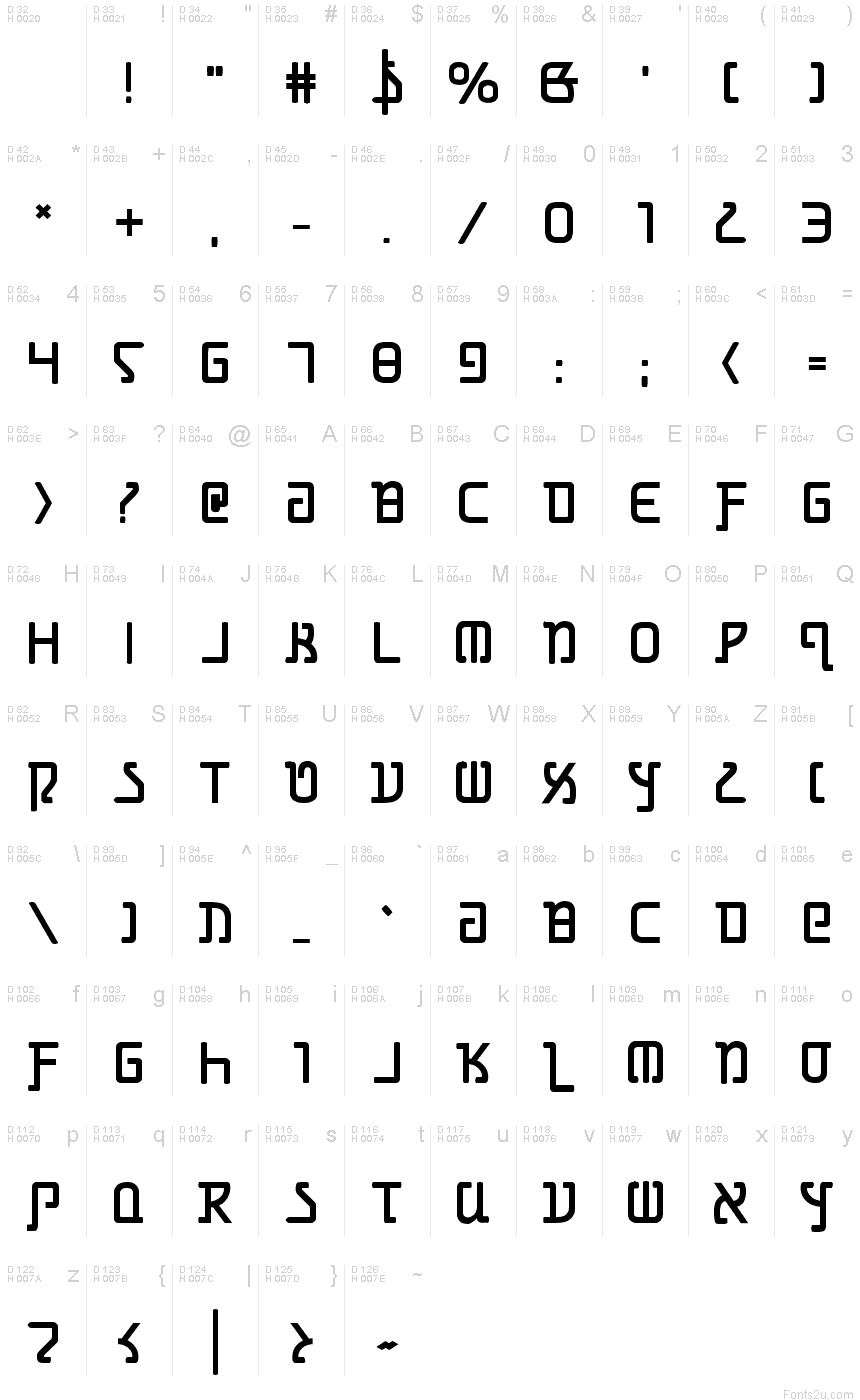
Grimlord Bold, progettata da Iconian Fonts, è un carattere display retro-futurista gratuito con lettere ampie e squadrate. Gli angoli esterni arrotondati incontrano tagli netti e strette interruzioni simili a stencil, conferendo alle lettere una struttura modulare e meccanizzata. I tratti densi e le giunzioni insolite ricordano i pannelli di controllo e l'hardware fantascientifico.
La grafica dei videogiochi rappresenta un contesto naturale per la sua geometria industriale, in particolare nelle etichette delle interfacce, nelle schermate dei titoli e nei poster promozionali. Si adatta inoltre al packaging di musica elettronica, al merchandising a tema tecnologico e alla segnaletica delle sale giochi, dove le forme segmentate possono richiamare diagrammi di circuiti, illustrazioni meccaniche o set di icone spigolose.
Grimlord Bold